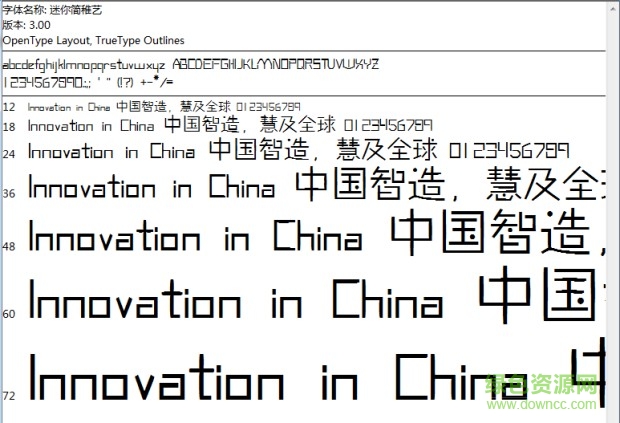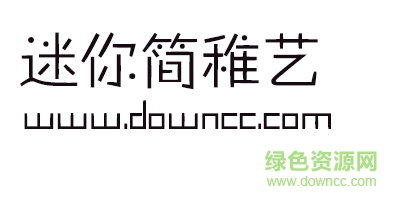
迷你簡(jiǎn)稚藝字體是主要應(yīng)用在印刷和廣告設(shè)計(jì)行業(yè)使用!這款字體很受廣大網(wǎng)友的喜愛(ài)!輸出的字體效果美觀、端正,字體比較清晰!喜歡的用戶歡迎下載安裝。
迷你簡(jiǎn)稚藝體是一款適用于廣告創(chuàng)意方面的迷你字體,能夠讓你的廣告字體效果更佳。有需要的朋友可以來(lái)綠色資源網(wǎng)下載使用!